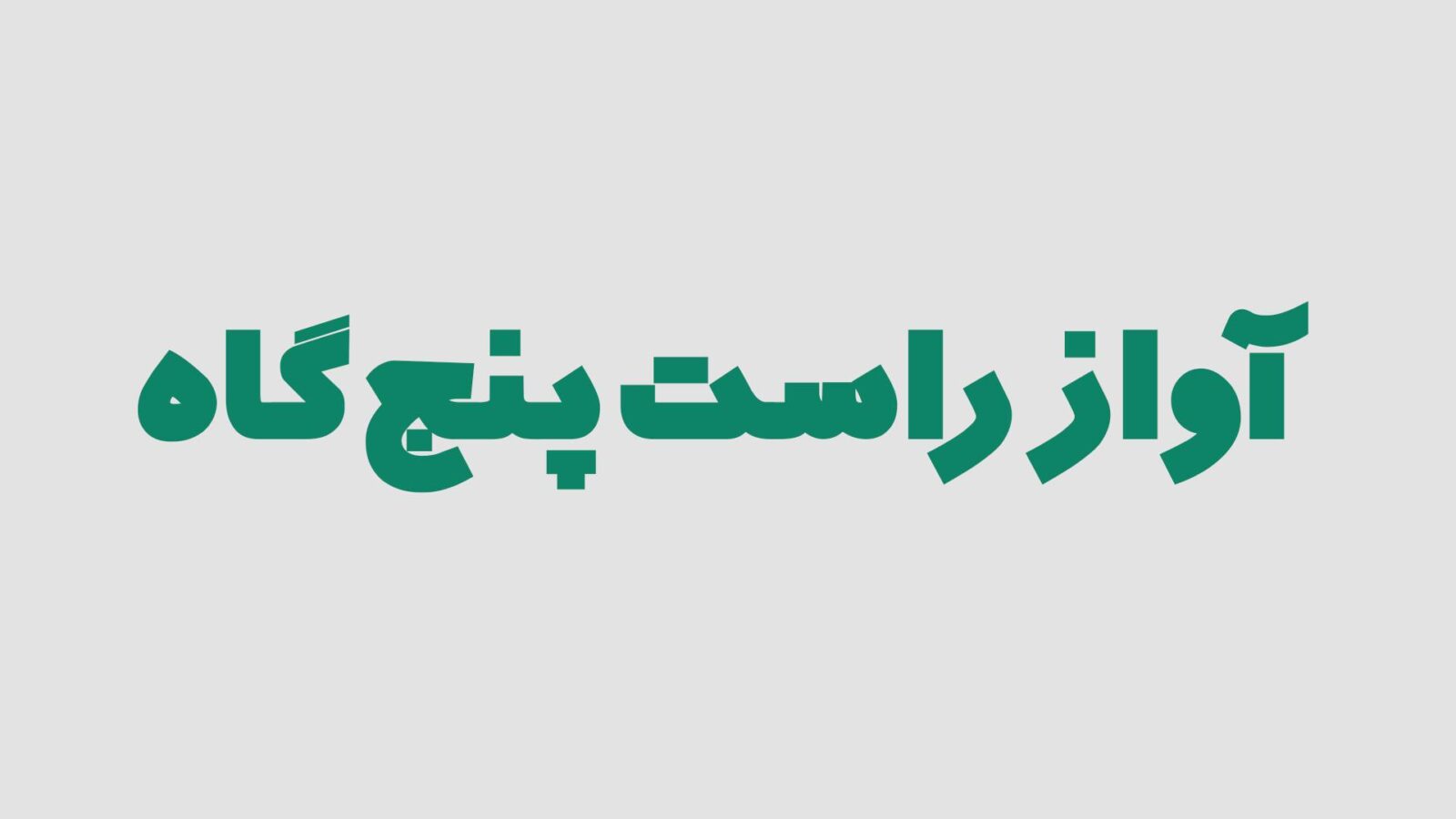
فونت جدید و زیبای تراشین
مدت‌هاست که واژه‌ی « فونت رايگان » جايگاه خود را در زبان فارسی کاملا از دست داده است. دليلش هم کاملا مشخص است، طراحی فونت کار دو سه هفته‌ ای نيست که يک طراح بيايد و تفريحی برای خودش فونت بسازد ! مشخصا طراحان فونت هم شب‌ ها شام می‌خورند و نياز دارند سالی چند بار لباس بخرند
امروزه همه‌ی اين کارها با پول انجام می‌شود
با همه‌ی اين تفاسير ، چرا اين فونت رايگان منتشر می‌شود ؟
بنده شاهین صباغ اولين فونت خود را در آبان 95 (پانزده سالگی) به صورت رايگان منتشر کردم. « ادوبی عربيک شين » که با استقبال نسبتا خوبی مواجه شد.
تِراشين يا همان ترافيک شين ، نسخه‌ی بسيار ضخيم شده‌ی فونت ترافيک می‌باشد.
فونت ترافيک، سال‌ها پيش توسط مصطفی اوجی طراحی شده است. شايد عده‌ای ايراد بگيرند که بنده حق تغيير و تصرف بدون اجازه را در اين فونت ندارم، حق هم دارند، اما به هرحال، فونت رايگان است و برای عموم.
ساخت تراشين، حداقل يک سال زمان برد. سعی شد که نسبت به ادوبی عربيک شين باگ‌های کمتری داشته باشد.